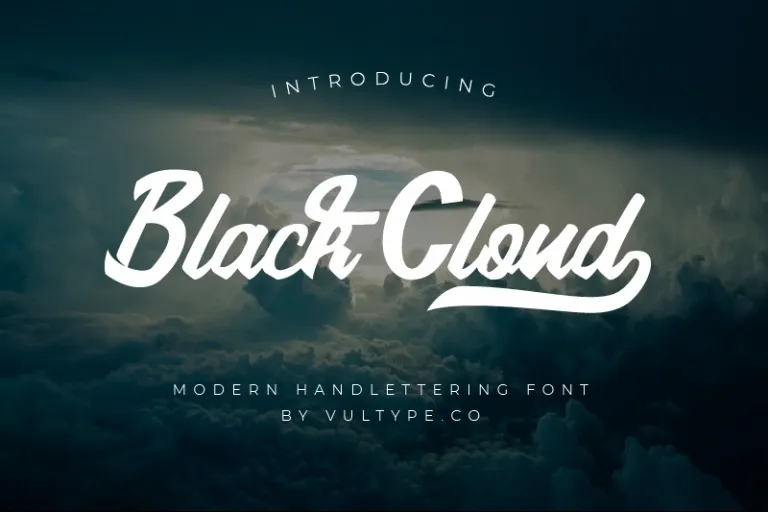
Black Cloud Script Font – Download Grátis
Esta nova fonte serifada é uma criação moderna com traços suaves de pincel, perfeitamente adaptável a uma variedade de ideias criativas. Ela traz um toque único e distintivo para projetos que você está desenvolvendo — seja em design gráfico ou impressão digital. A Black Cloud Script Font é ideal para aqueles desejando introduzir um toque moderno ao seu trabalho sem perder a elegância necessária. Suas linhas fluidas e arredondadas garantem um design sofisticado que se adequa a diversos estilos de criação, tornando-a uma excelente opção para designers buscando inovação em cada projeto. Adicione essa fonte à sua galeria de ideias criativas e observe como ela lhe ajudará a destacar no meio do campo. Não importa o tipo de design que você está trabalhando ou qual é seu público-alvo, esta fonte será um aliado útil para garantir uma impressão distintiva em cada trabalho apresentado.